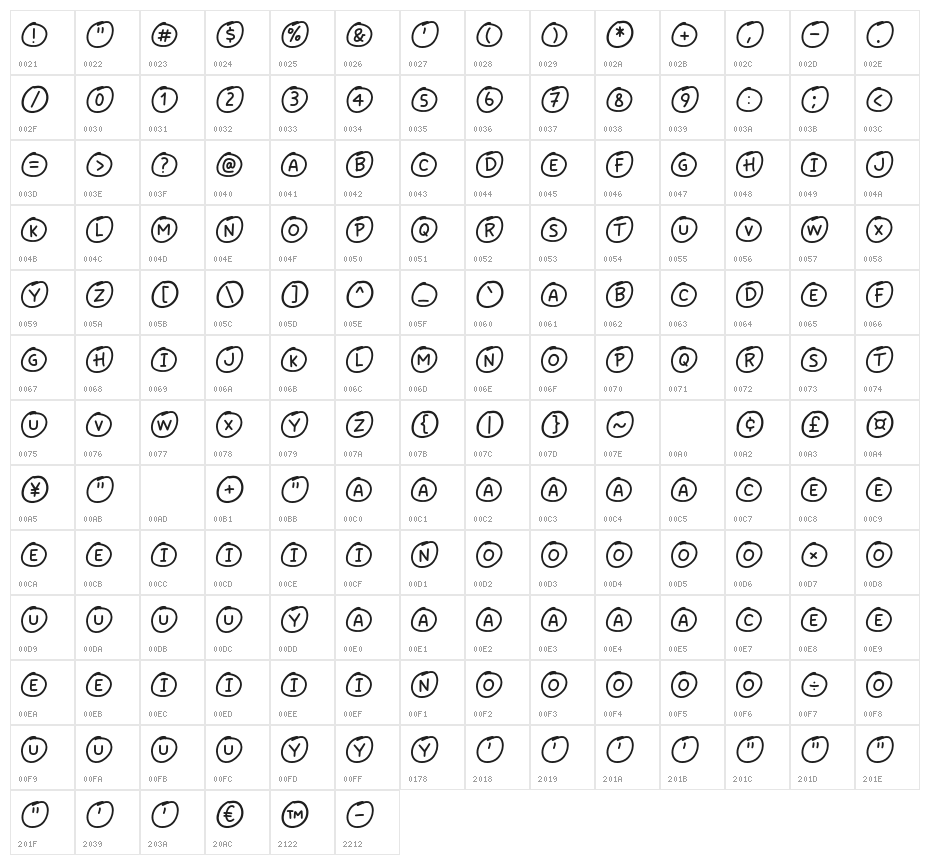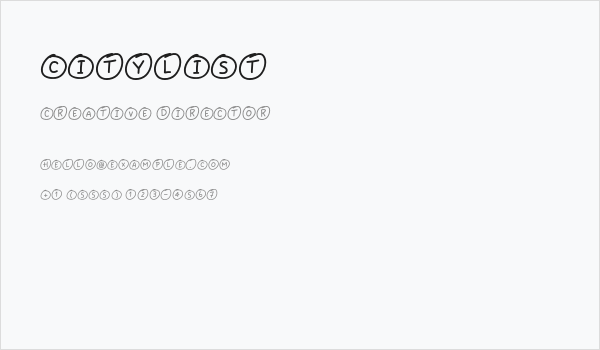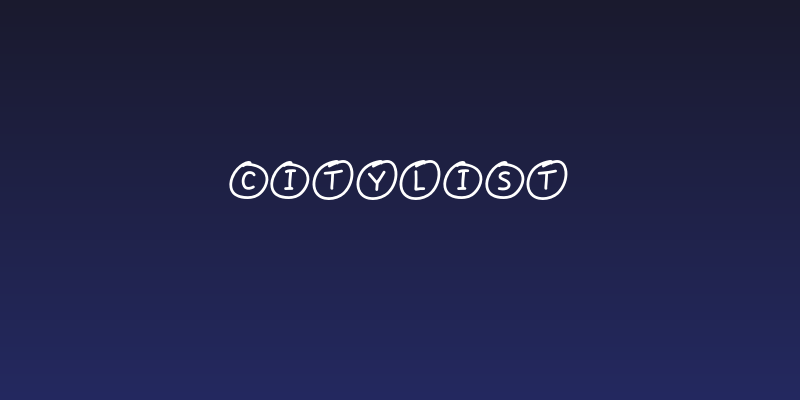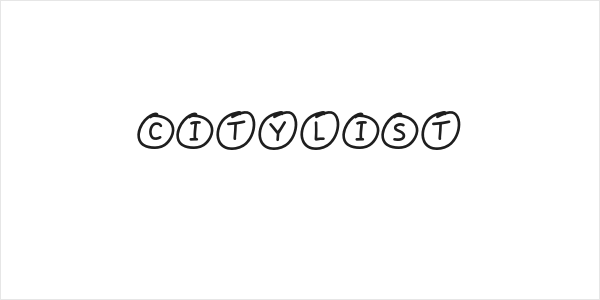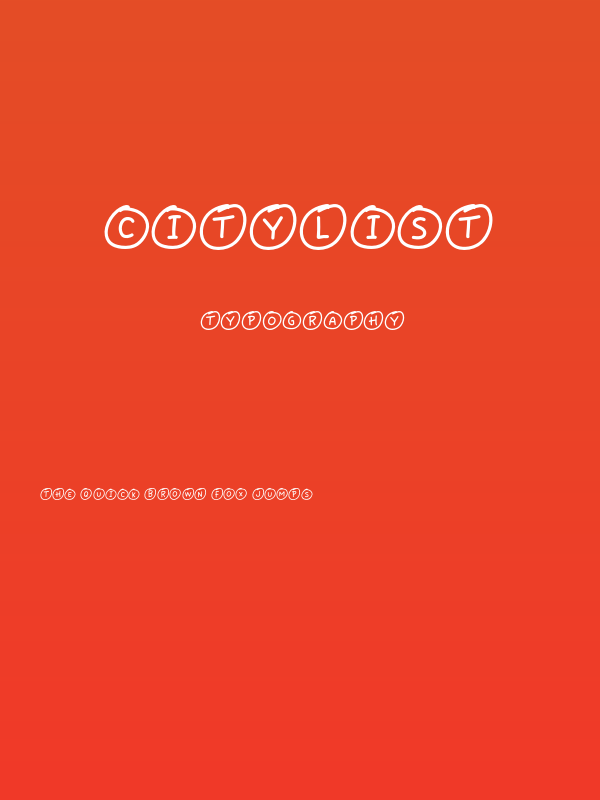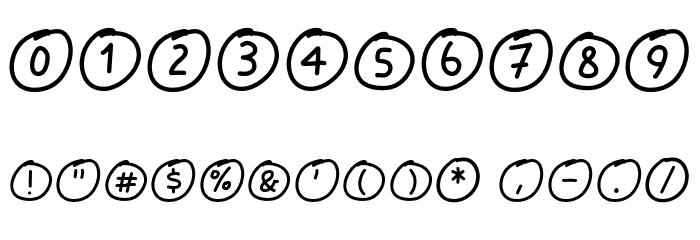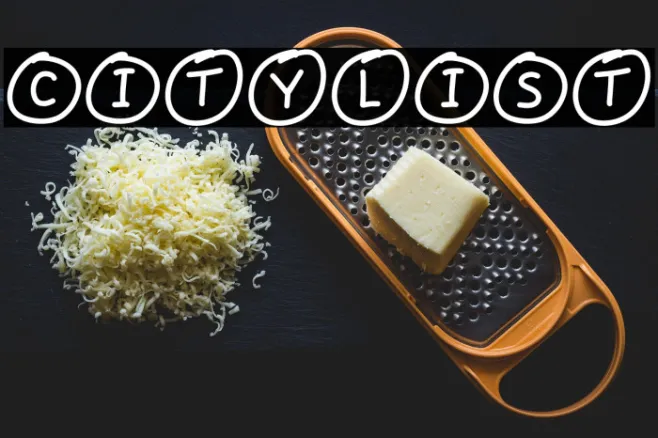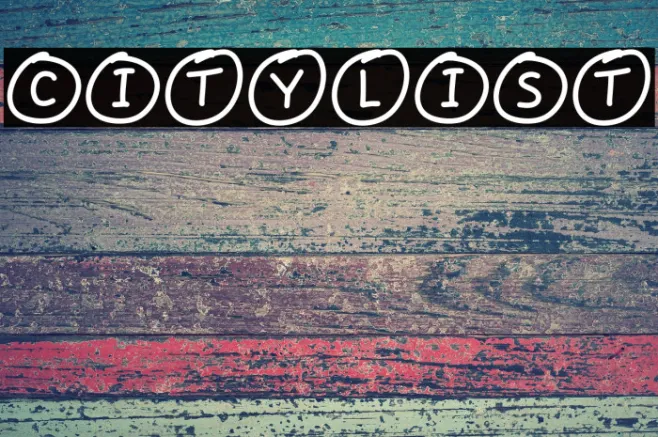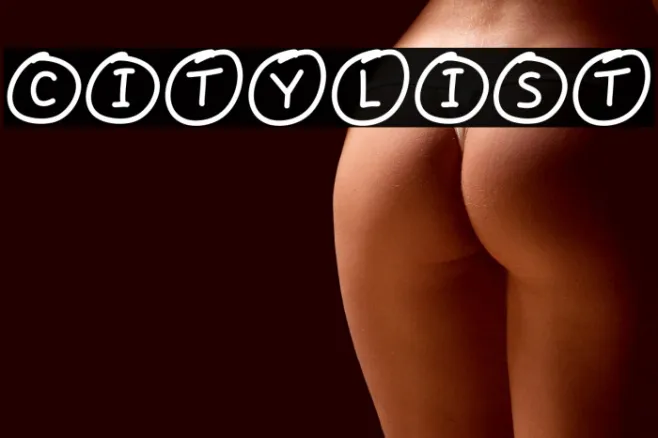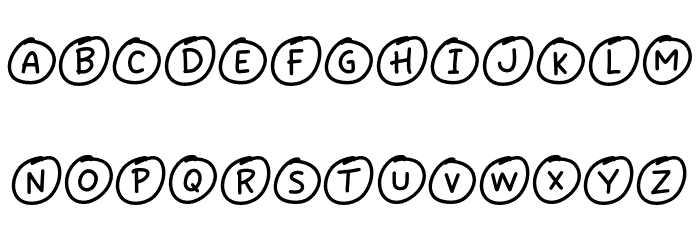
Citylist Font
Fonts by Khurasan
| Vorgeschlagene Projekte | Ideal for children's books, greeting cards, playful branding, and casual event invitations. |